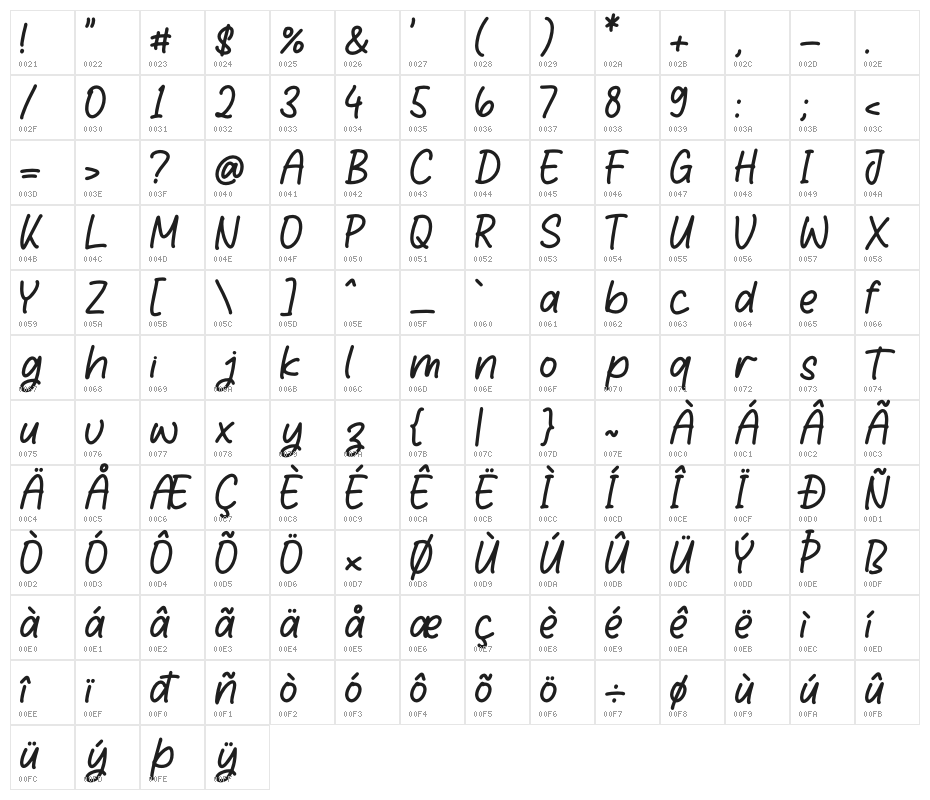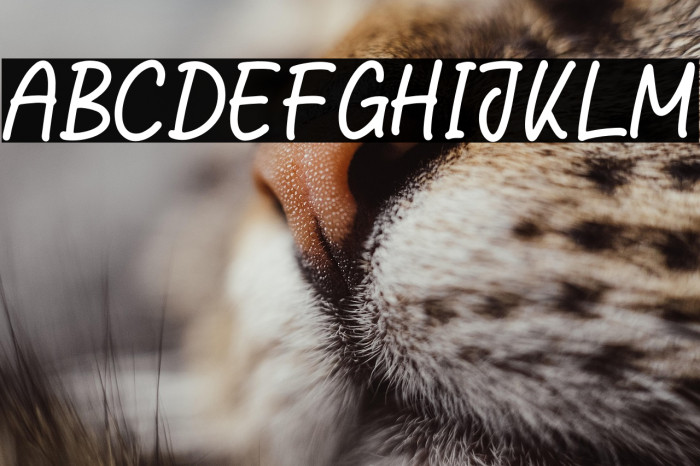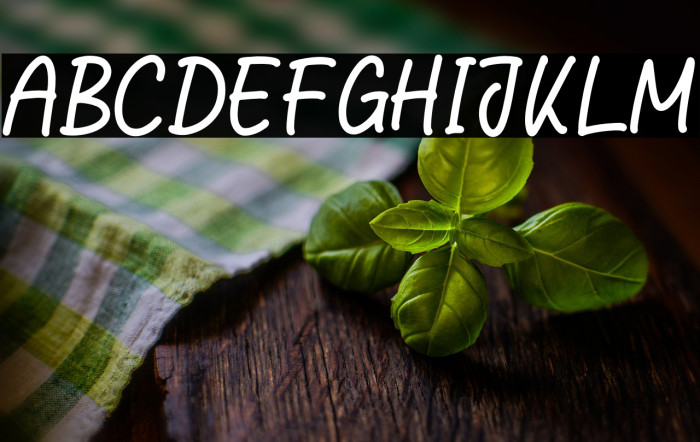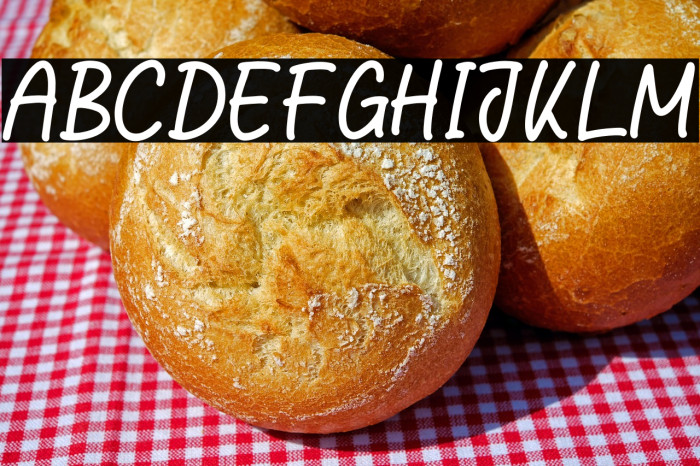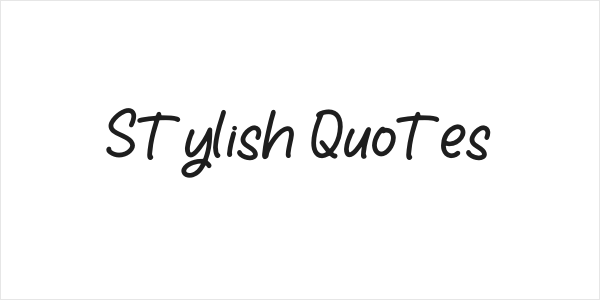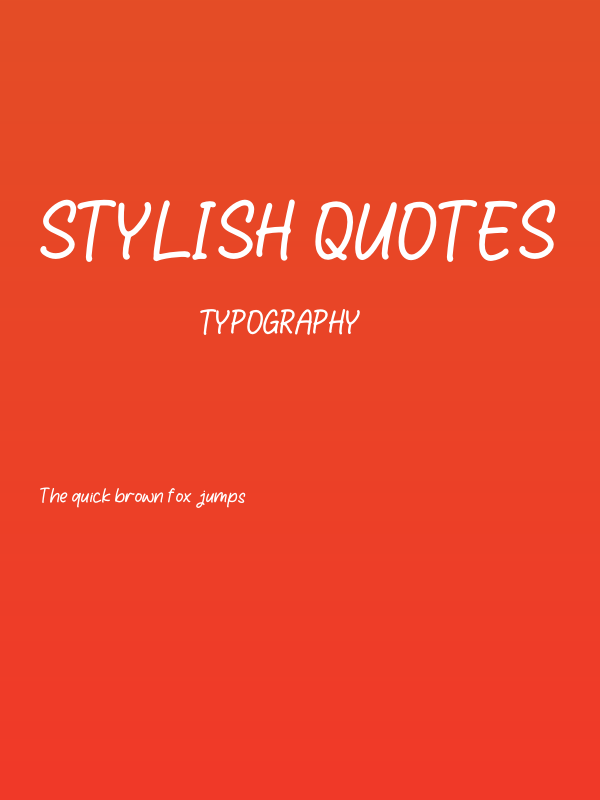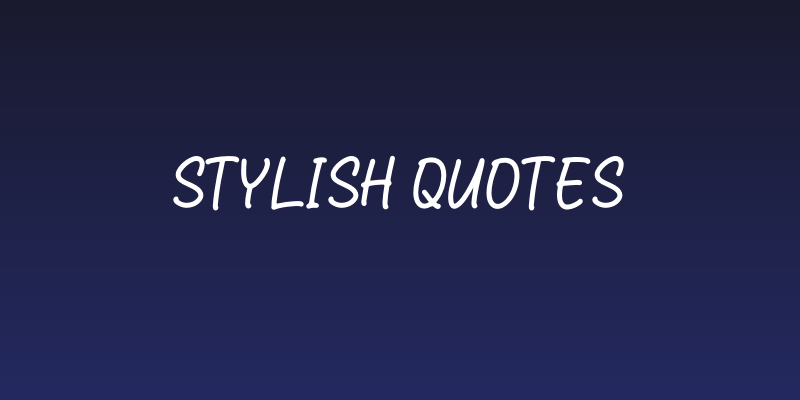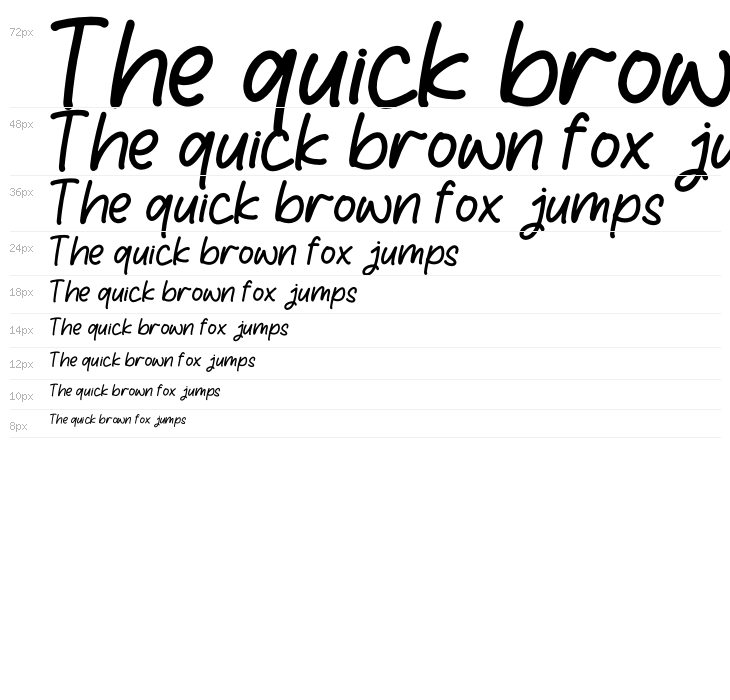
Stylish Quotes Font
| Stile generale | Casual, Playful |
| Caso d'uso | Headlines, Informal text, Creative projects |
| Progetti proposti | Ideal for greeting cards, personal branding, social media graphics, and informal invitations. |